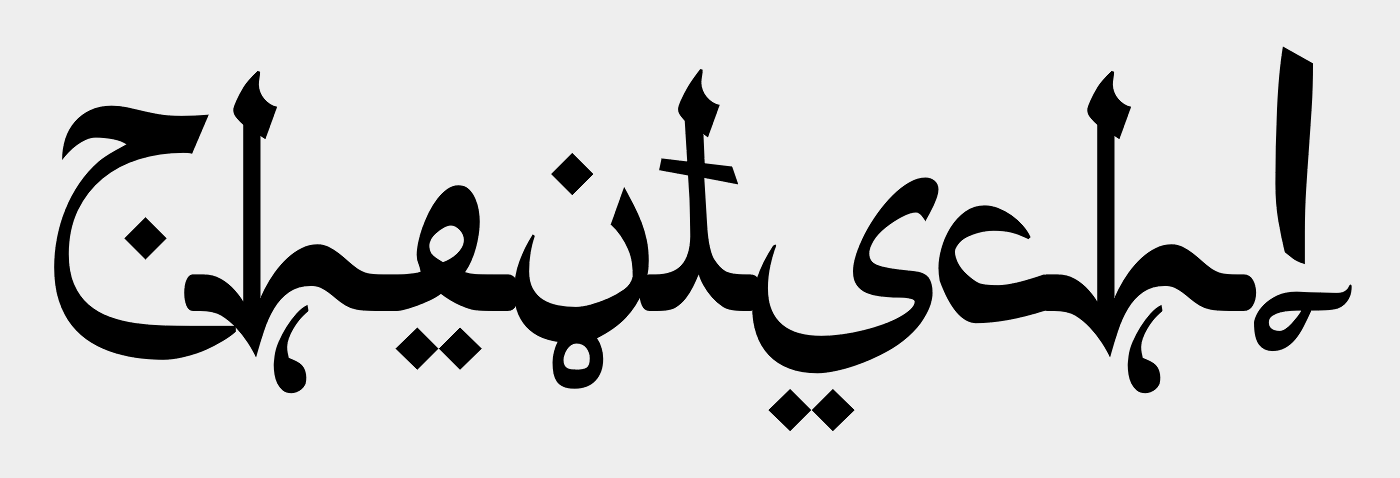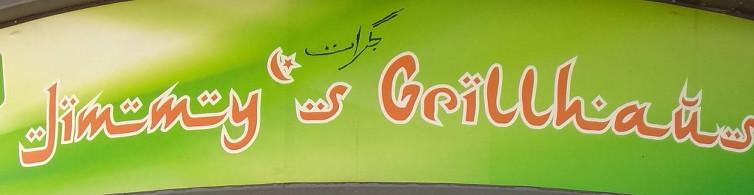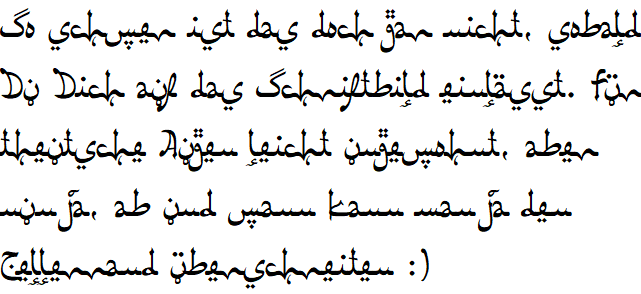
Arabisierte Schrift für PC
Ich erstelle gerade einen Video in Marrakesch gedreht. Dafür würde ich gerne eine Schrift verwenden, die die lateinischen Buchstaben in arabisierter Form darstellt. Gibt es so etwas? Und wenn ja, wie heißt sie und wo kann ich sie downloaden.
Schau mal hier: https://www.dafont.com/theme.php?cat=202
Ob das aus gestalterischen Gesichtspunkten wirklich sein muss, bleibt aber dir überlassen …
Mit dem längeren Text ist es tatsächlich ganz leicht. Der Deep-Learning-Algorithmus  braucht einfach mehr Input. :tutor:
Was die ursprüngliche Idee angeht, bin ich wohl ähnlich skeptisch wie bertel. Der Einsatz solcher Pseudoalfabete kann manchmal funktionieren. Von einem der m.E. wenigen Beispiele hier ein Foto:
Aber da transportiert das Pseudoarabische auch eine ganz klare Botschaft: Hier gibt es explizit arabische (oder wenigstens arabisch inspirierte) Küche – etwas, das aus dem Namen der Bude nicht hervorgeht. Und so ein D̸ö̸n̸e̸r̸- …, äh, Schawarma-Stand muss sich auch nicht so bierernst nehmen, sondern kann sich gern auch mal eine augenzwinkernde Identität geben.
Diese Selbstpersiflage, die sich m.E. bei solchen Alfabeten geradezu aufdrängt, ist das eine Wirkung, die du mit dem Film(titel) auch erzielen  möchtest?
Der Einsatz solcher Pseudoalfabete kann manchmal funktionieren.
Wenn man nur nicht einen sogenannten Deppenapostroph eingebaut hätte (der noch dazu falsch herum gebogen ist).
Ich persönlich würde eher ganz normale lateinische Schrift in arabische Rahmen setzen, so etwas ähnliches, wie es z.B. such für z.B. Koranseiten verwendet wird.